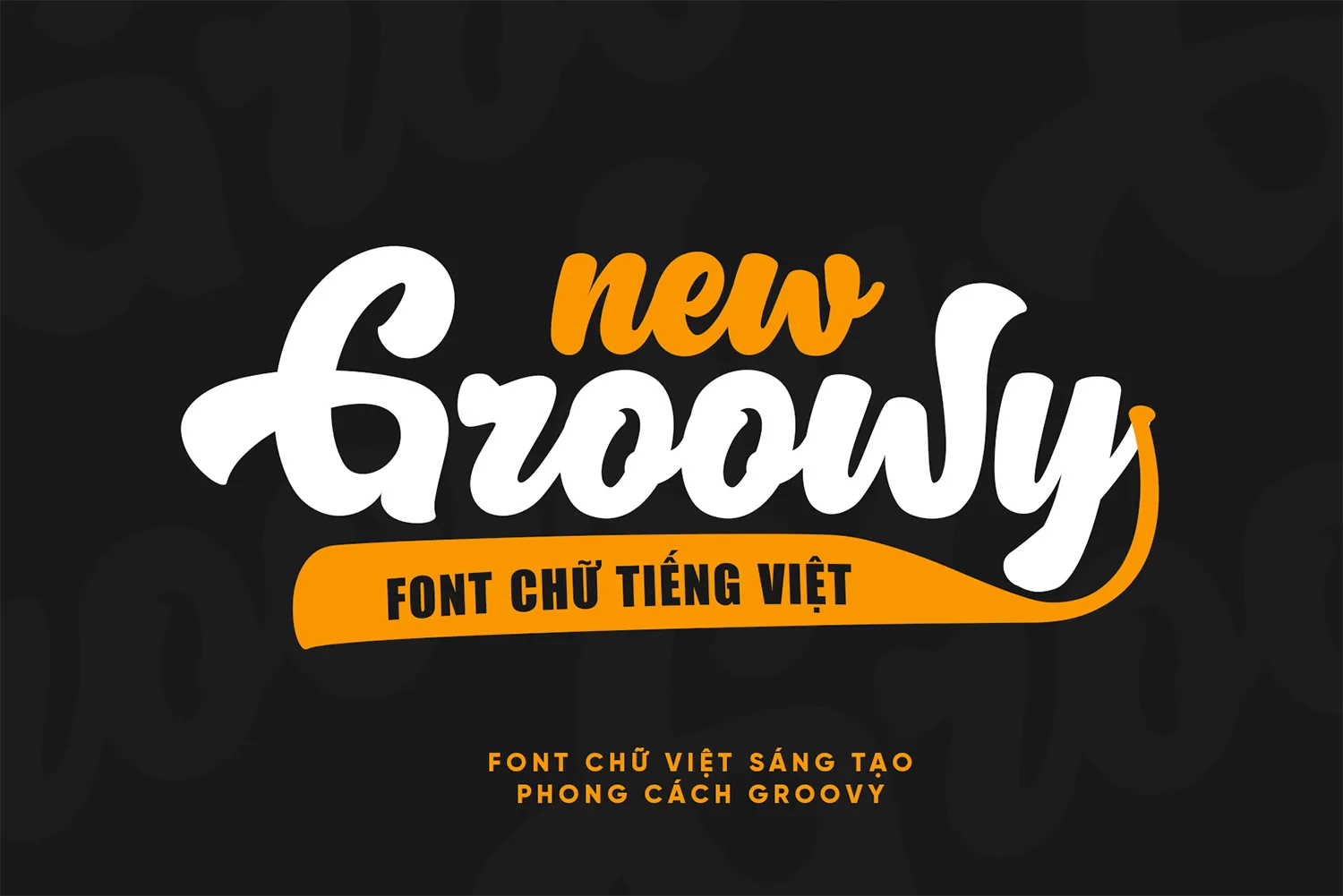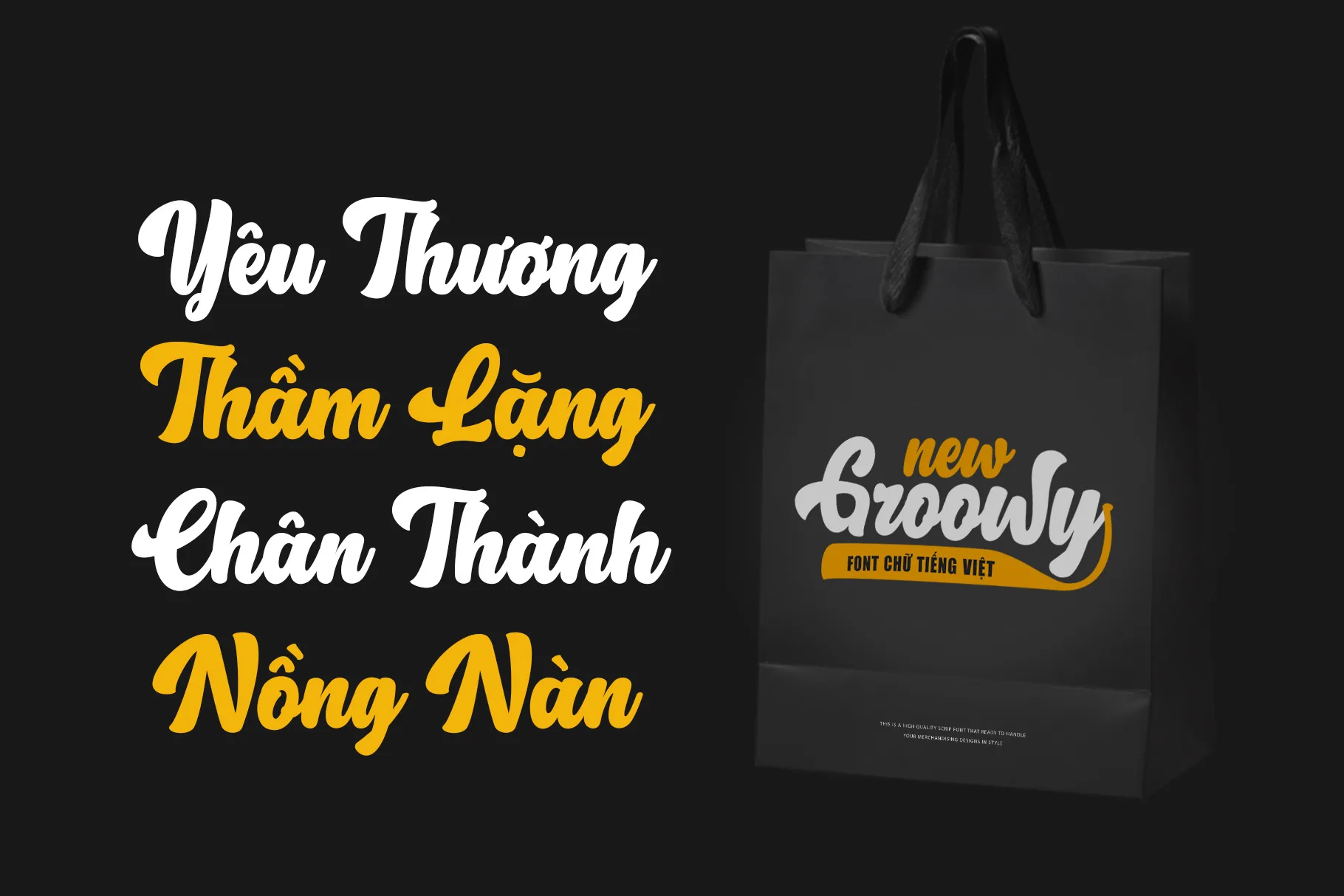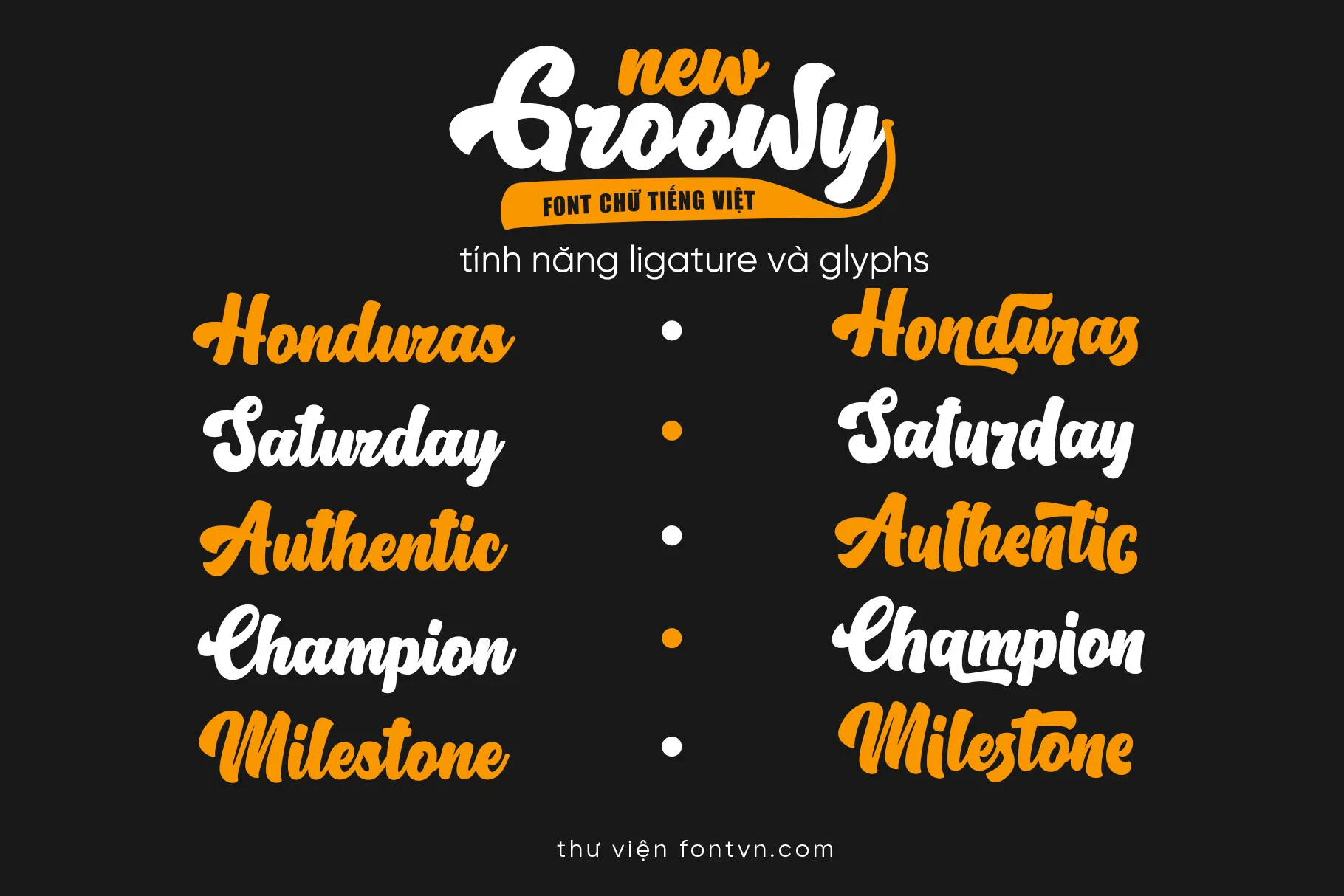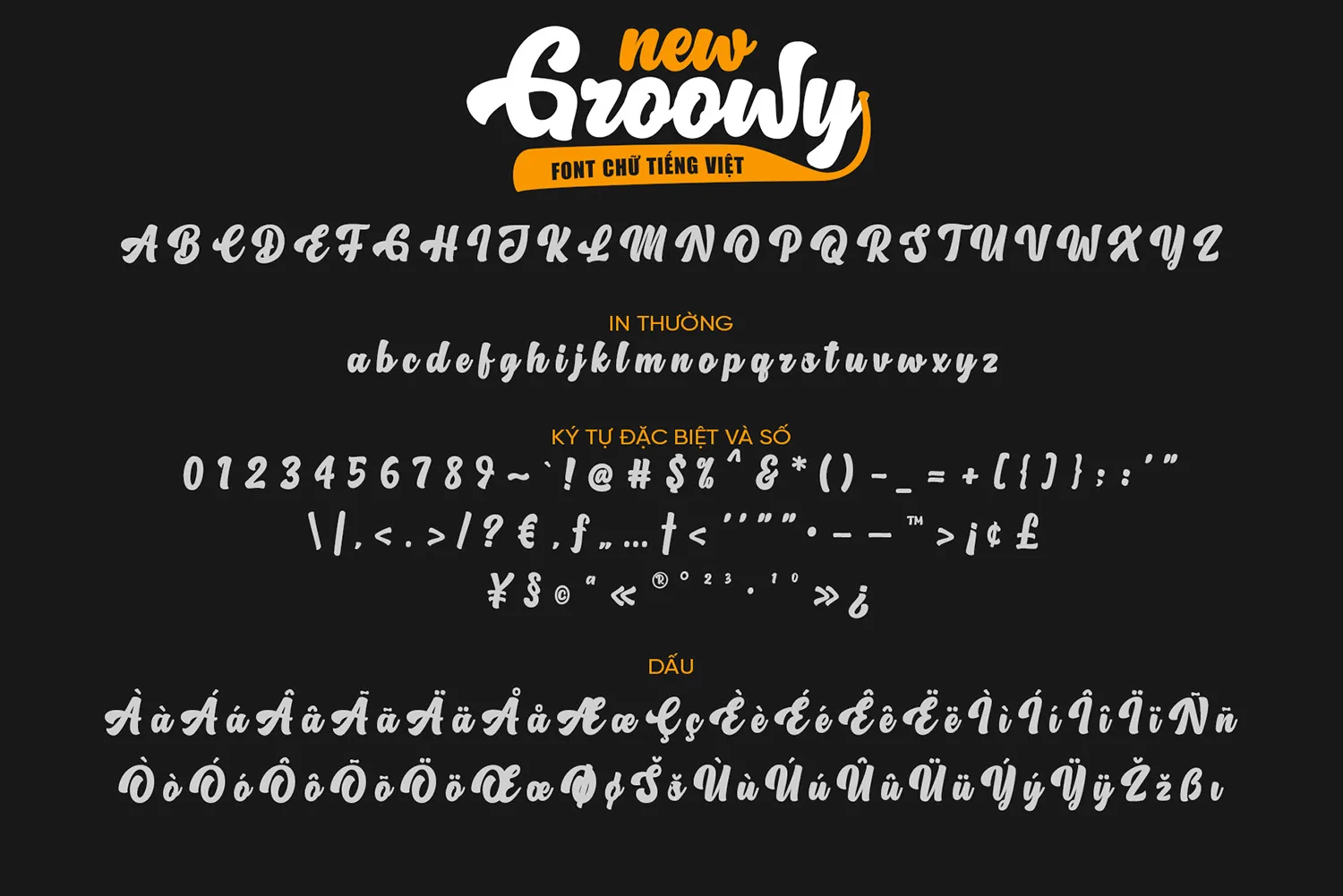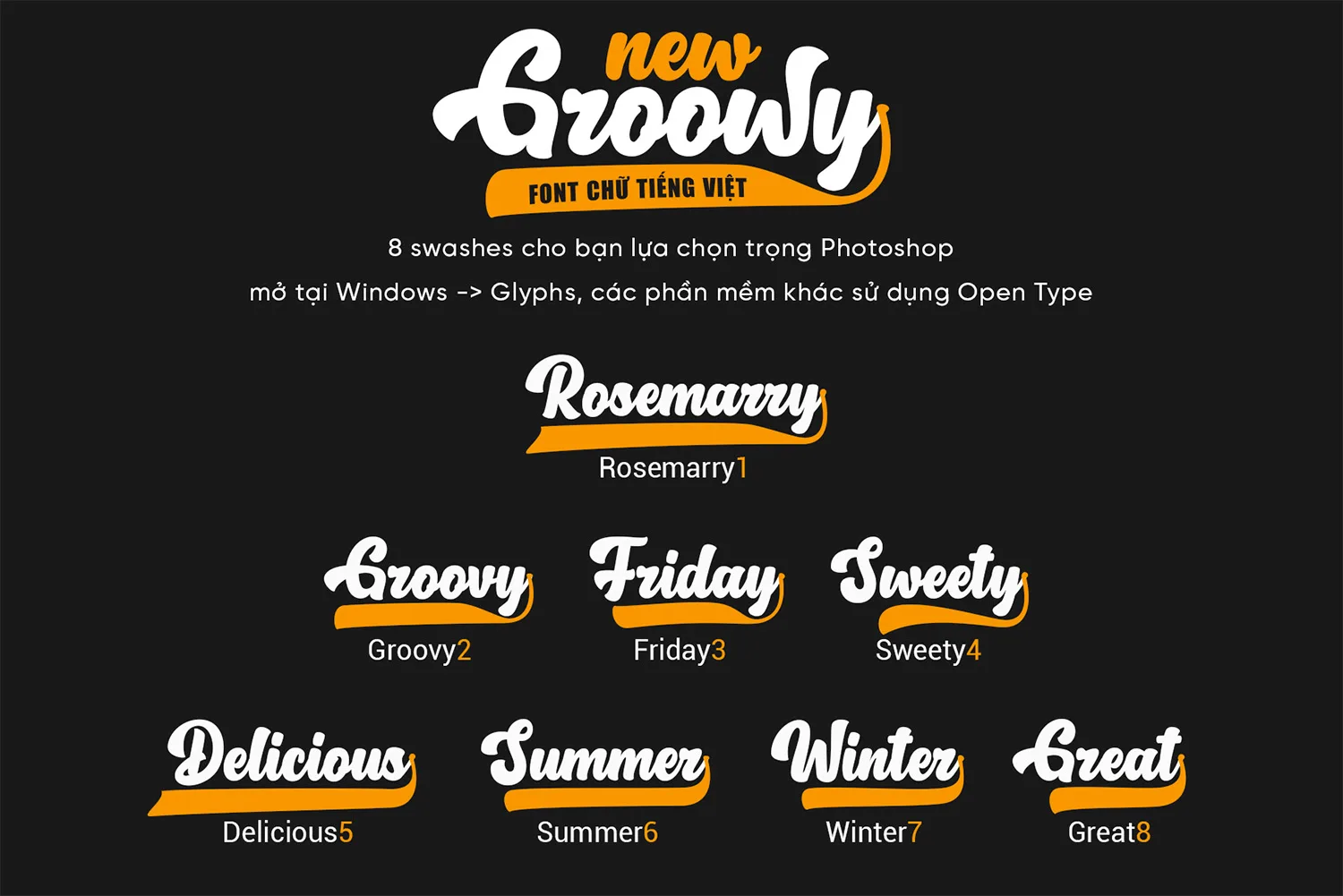
DVN Groowy tiếng Việt – Font Chữ Script Sáng Tạo Phong Cách Groovy
DVN Groowy là font chữ script phong cách groovy do chính bạn thiết kế, mang lại cảm giác vui tươi, phóng khoáng và đầy năng lượng. Với những đường nét bo tròn mềm mại, kết cấu chữ mượt mà và tinh thần retro hiện đại, DVN Groowy giúp các thiết kế trở nên nổi bật ngay từ cái nhìn đầu tiên.
Font hỗ trợ tiếng Việt đầy đủ, được tối ưu từng chi tiết để đảm bảo khả năng hiển thị đẹp và cân đối trên mọi kích cỡ. Đây là lựa chọn hoàn hảo cho các dự án đòi hỏi sự sáng tạo và cá tính như thiết kế logo, tiêu đề poster, áo thun, bao bì sản phẩm, banner mạng xã hội, hoặc bất kỳ layout nào cần tạo điểm nhấn thị giác mạnh mẽ.
DVN Groowy kết hợp vẻ hoài cổ đặc trưng của thập niên 70 với phong cách thiết kế hiện đại, tạo nên một chất riêng khó nhầm lẫn. Nếu bạn đang tìm một font script mang lại cảm giác “funky”, vui nhộn và đầy chất nghệ, DVN Groowy chính là công cụ giúp ý tưởng của bạn tỏa sáng.